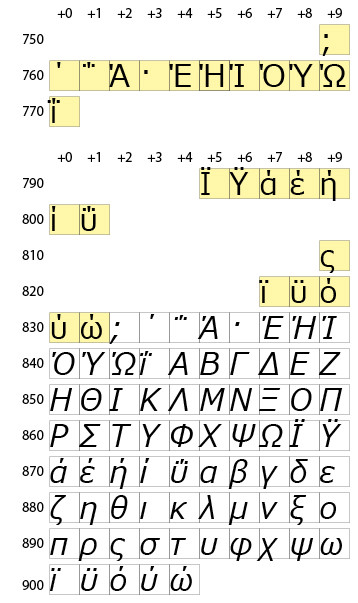
メイリオにはどんな文字が入っているのか
- 前回のエントリでは、メイリオに含まれる漢字集合がAdobe-Japan1-5のそれと一致することを述べた。今回はメイリオに含まれる全グリフを対象として、それがAdobe-Japan1-5にも含まれるかどうかを確認してみた。
- 結果。ひとつひとつのグリフについてきちんと見たわけではないが、メイリオのグリフセットは、Adobe-Japan1-5の上位集合であり、約300の独自のグリフを追加したもののようだ。以下、メイリオにあってAdobe-Japan1-5にないグリフを列挙する。
- スモールキャプス(グレー地)、オールドスタイル数字(ブルー地)など(下図)。
- 上図白地の通貨記号などは、オールドスタイル数字に合わせるためのものだろうか。下図では、これらを汎用のプロポーショナルグリフと比較してみた。それぞれが微妙に異なっていることがわかる。
- ダイアクリティカルマーク付きのギリシア文字、ギリシア文字のイタリックなど(下図)。
- 上図のグリフのうちGID+819は、GID+16586に全角のヴァリアントを持つ。ここでは(GID/CID順の前後関係を尊重して)GID+16586のほうをAdobe-Japan1-5のCID+16222と対応付け、GID+819を「Adobe-Japan1-5に含まれないグリフ」として扱った。ただし、Unicodeマッピングの面からは、メイリオのGID+819とAdobe-Japan1-5のCID+16222が、U+03C2 GREEK SMALL LETTER FINAL SIGMAを介して対応する(下図)。
- キリル文字のイタリック(下図)。
- 下図、GID+20682の円記号は、U+005C REVERSE SOLIDUSに対応するもの。このあたりの事情については、安岡さんの「YEN SIGN問題縁起」を参照。GID+20683は、U+005Cのイタリックという位置づけなのだろう。GID+20681は、もしかするとWindowsユーザにとっては親しみのある記号なのかもしれないが、わたしには何だかわからない。ご存知の方は、ぜひコメントを。
- 最後に、メイリオのGIDに対してAdobe-Japan1-5のCIDを対照させた表(わたしが目で見比べて手動で入力したもの)を載せておく。「メイリオのGID」のうち括弧で括ったのは、未定義(空き)のもの。
| メイリオのGID | Adobe-Japan1-5のCID |
|---|---|
| 0 | 0 |
| (1-2) | |
| 3-232 | 1-230 |
| 233-616 | 9354-9737 |
| 617-770 | 該当なし |
| 771-794 | 1011-1034 |
| 795-801 | 該当なし |
| 802-818 | 1035-1051 |
| 819 | 該当なし | 820-826 | 1052-1058 | 905-911 | 1059-1065 | (912-924) | 925-983 | 1066-1124 | (984-998) | 999 | 該当なし | (1000-1012) | 1013-1077 | 該当なし | (1078-1092) | 1093-1494 | 231-632 | 1495-1535 | 9738-9778 | 1536-1560 | 12063-12087 | 1561-1769 | 633-841 | 1770-1771 | 8718-8719 | 1772-2303 | 15444-15975 | 2304-2472 | 842-1010 | 2473-5437 | 1125-4089 | 5438-8825 | 4090-7477 | 8826-9631 | 7478-8283 | 9632-9706 | 8284-8358 | 9707-10065 | 8359-8717 | 10066-10699 | 8720-9353 | 10700-12983 | 9779-12062 | 12984-16339 | 12088-15443 | 16340-20680 | 15976-20316 | 20681-20683 | 該当なし |